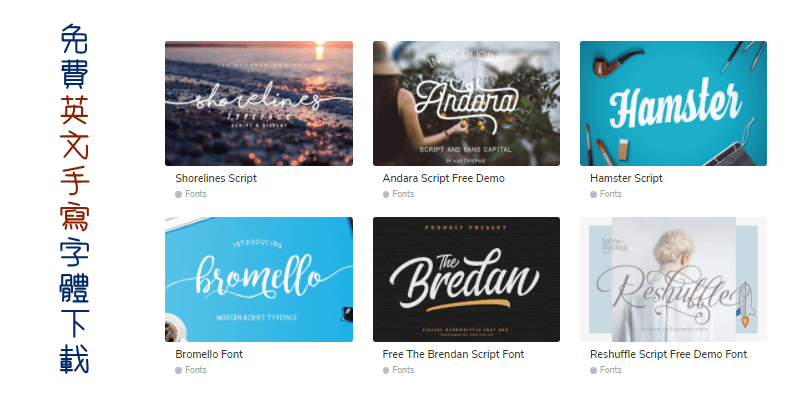
Free Fonts超過600+個免費英文手寫字體下載,可個人與商用!100%免費的高質感字體,有手繪風、草寫、簽名字體、筆刷等藝術風格的英文字型,安裝到電腦中後,可以應用在PhotoShop美圖、製作PPT簡報或是設計各種社群軟體的圖片,為作品添加好看又吸睛的文字。(延伸閱讀:推薦6個免費英文字體下載網站,你要找的英文字型都在這!)
Free Fonts 免費英文手寫字體下載
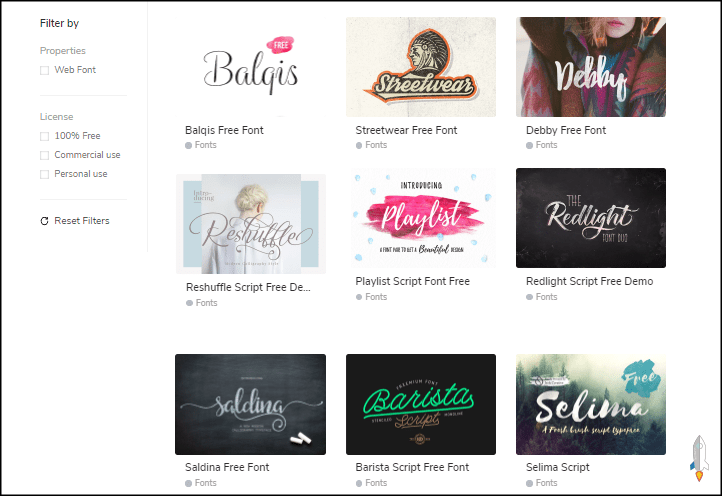
草寫風的英文字體,點一下Download即可下載到電腦中。
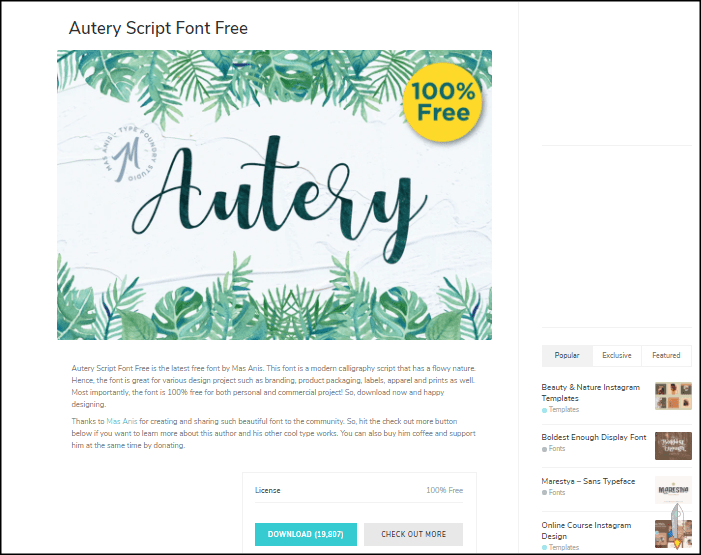
手寫英文字體。
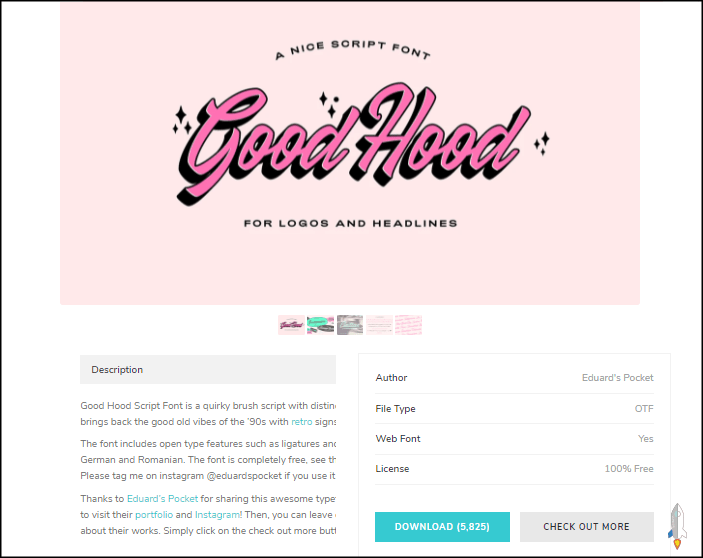
簽名英文字體,多達600+個英文字型,免費安裝使用,可個人與商用。